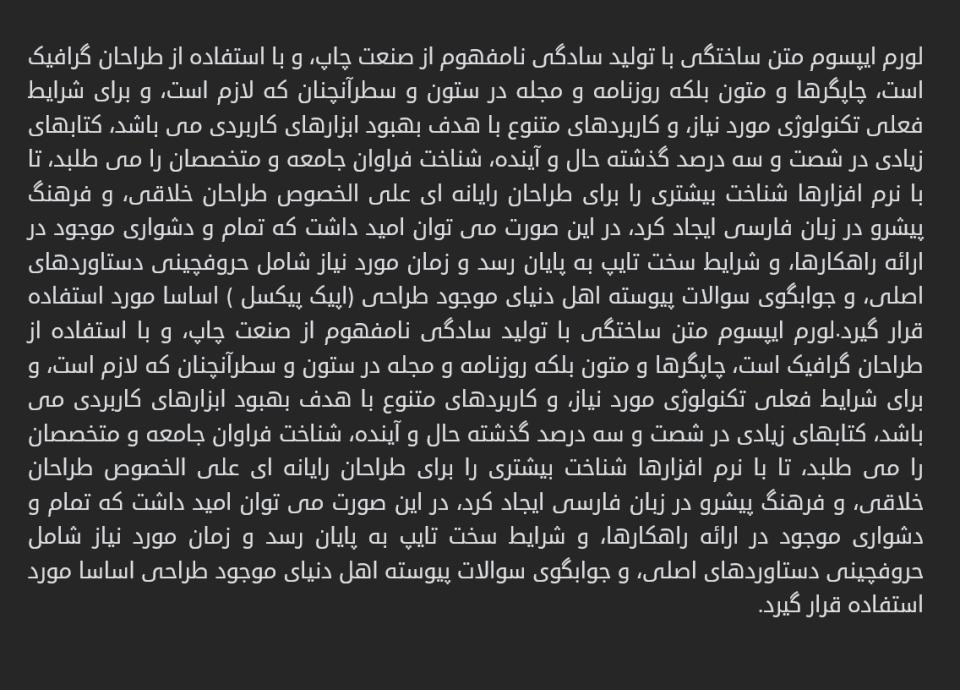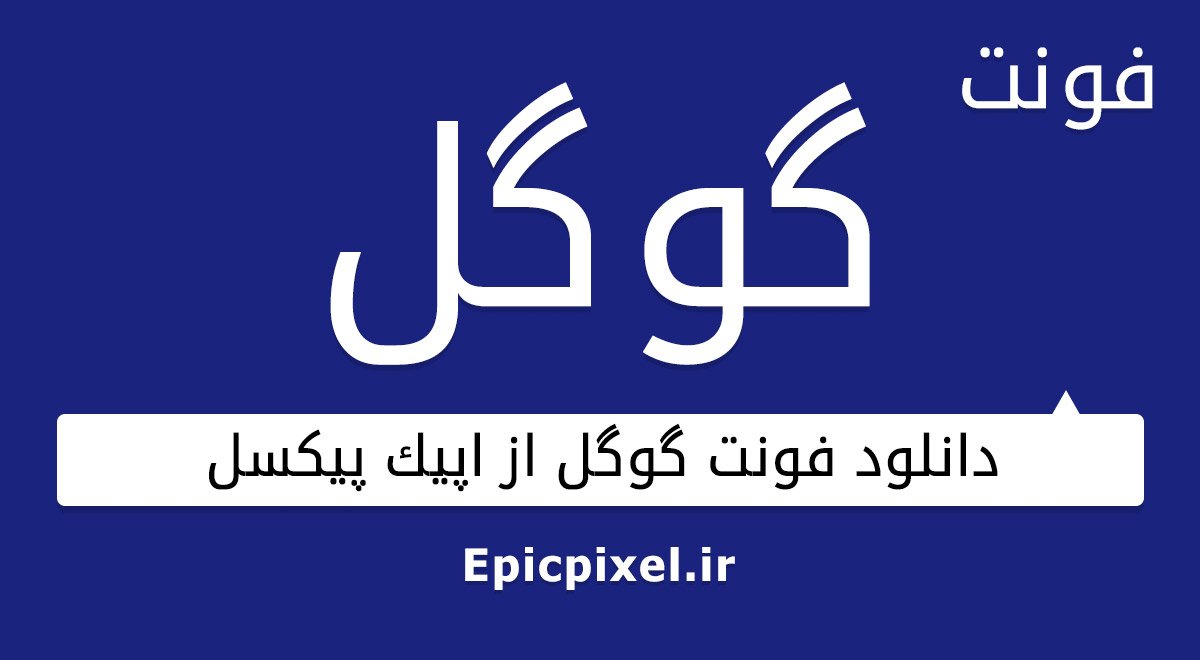
فونت گوگل فارسی
برای داشتن طراحی های حرفه ای و منحصر به فرد، با ظاهری مدرن و خوانا، بدون نیاز به پرداخت هزینه، دانلود فونت های فارسی گوگل بهترین گزینه است. این فونت ها با پشتیبانی از تمامی حروف فارسی، در انواع نرم افزارهای طراحی قابل استفاده بوده و به شما کمک می کنند تا پروژه های گرافیکی خود را با کیفیت بالا اجرا کنید.
به عبارت دیگر، با دانلود فونت گوگل فارسی، به یک ابزار قدرتمند و رایگان برای زیباتر کردن طرح های خود دسترسی پیدا خواهید کرد.